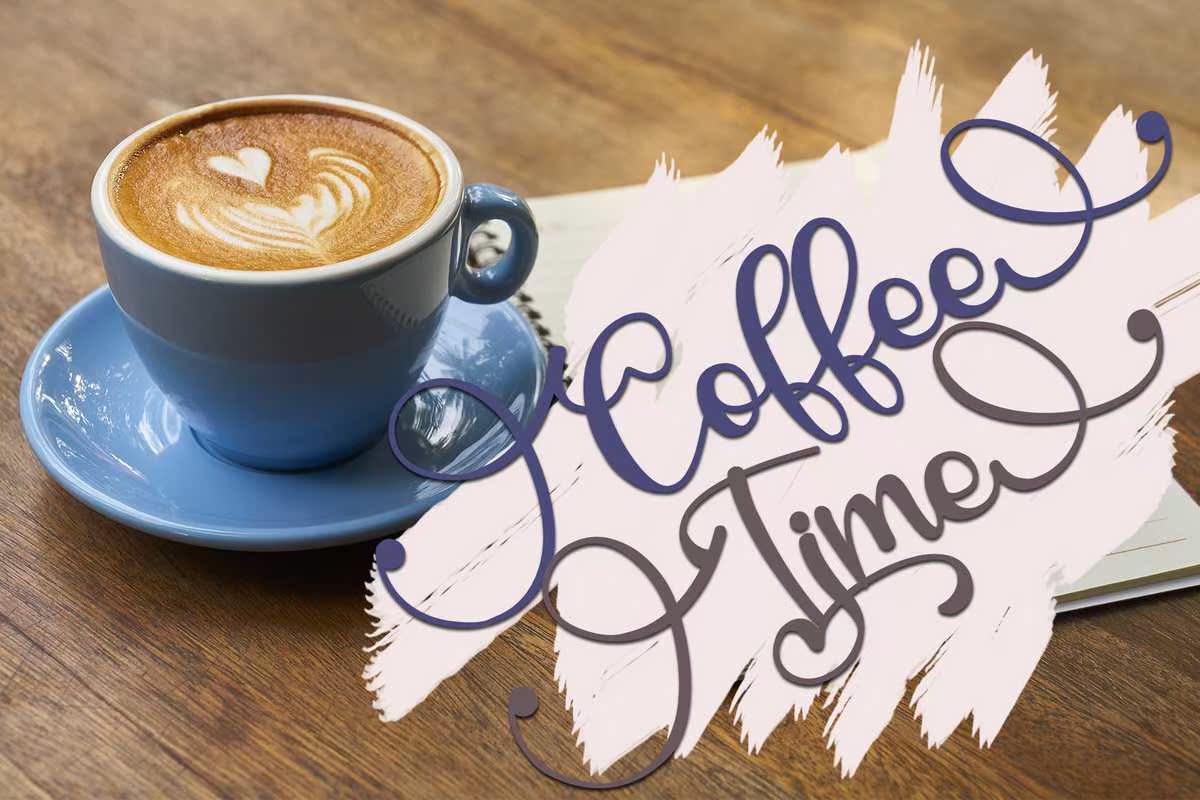
BiterLove Fonts是一款现代化的AlligraphyFontBylettRafaStudio。它具有流动的字母,可使您的设计更具吸引力,并具有许多灵活的字符。BiterLove Fonts是完美的;徽标、问候卡、包装设计、耐磨性、工艺设计、任何项目、书名、婚礼宣传、包装等。BiterLoveFont是现代的AlligraphyFontByletterRafaStudio。它具有流动的字母,可以让您的设计更具吸引力,并且可以看到许多生动的字符。BiterLoveFontIsPerfect;徽标、问候卡、包装设计、耐磨性、工艺设计、任何项目、书名、婚礼宣传、包装等。